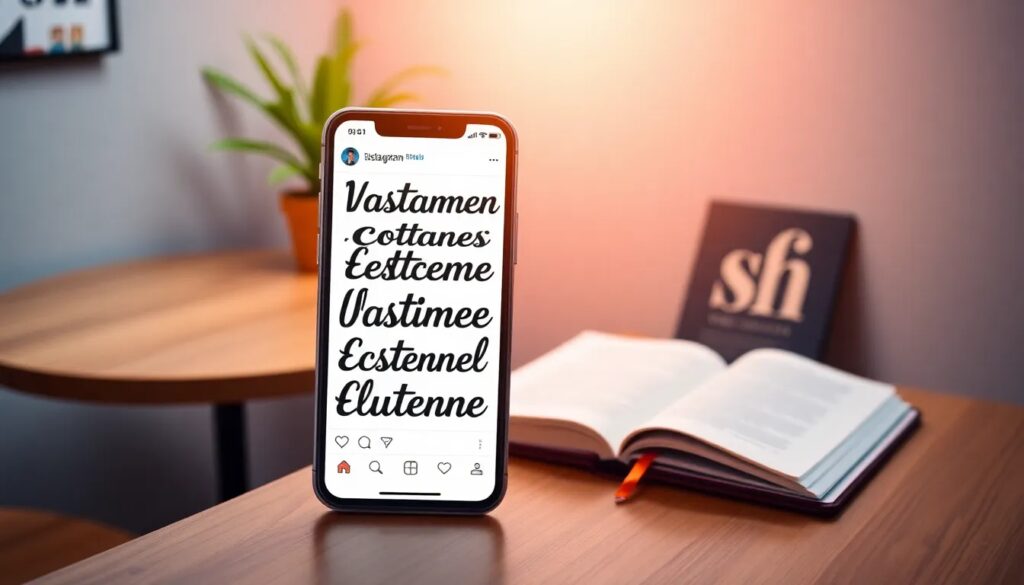
Tipografía en Instagram: cómo usarla y personalizarla
La tipografía en Instagram es un elemento esencial para destacar en esta plataforma visual. Usar diferentes estilos de texto puede ayudar a que tus publicaciones sean más atractivas y memorables. A través de diversas herramientas y aplicaciones, es posible personalizar la tipografía para que se ajuste a tu estilo personal o de marca.
En este artículo, exploraremos cómo funciona el conversor de letras para Instagram, los tipos de letras más populares, y las mejores aplicaciones para cambiar fuentes. También te daremos ideas creativas para usar tipografías que capturen la atención de tus seguidores.
¿Cómo funciona el conversor de letras para Instagram?
El conversor de letras para Instagram es una herramienta en línea que permite transformar tu texto en diferentes estilos tipográficos. Este tipo de herramientas utiliza el sistema Unicode para generar variaciones que son compatibles con Instagram y otras redes sociales.
Al utilizar un conversor, simplemente escribes el texto que deseas transformar y, en cuestión de segundos, obtendrás varias opciones de estilos para elegir. Estas transformaciones pueden incluir cursivas, negritas, y símbolos especiales. Una vez que decides el estilo que más te gusta, solo tienes que copiarlo y pegarlo en tu publicación de Instagram.
Además, muchos de estos conversores son gratuitos y no requieren registro, lo que los hace accesibles para cualquier usuario. Su uso se ha popularizado especialmente entre quienes buscan añadir un toque de creatividad a sus publicaciones.
¿Qué tipos de letras son las más usadas en Instagram?
En Instagram, algunas de las tipografías más usadas incluyen estilos cursivos, negritas y letras decorativas. Estas tipografías no solo aportan un estilo único, sino que también son fáciles de leer en dispositivos móviles. A continuación, te presentamos una lista con los tipos más populares:
- Cursivas: ideales para dar un toque elegante.
- Negritas: perfectas para enfatizar un mensaje.
- Decorativas: aportan un estilo único y divertido.
- Minimalistas: limpias y fáciles de leer.
- Vintage: evocan nostalgia y son muy llamativas.
La elección del tipo de letra también puede depender del mensaje que deseas transmitir. Por ejemplo, si estás promocionando un producto, una tipografía clara y moderna puede ser la más efectiva. En cambio, si deseas compartir una cita inspiradora, una letra cursiva puede añadir un toque especial.
¿Cómo personalizar fuentes de Instagram?
Personalizar la tipografía en Instagram es una forma efectiva de destacar tu contenido. Existen varias maneras de hacerlo, y aquí te mostramos algunas de las más populares:
- Utilizar generadores de fuentes en línea: como los conversores, te permiten crear texto único rápidamente.
- Apps de edición: aplicaciones como Canva o Over ofrecen herramientas de diseño que incluyen diversas tipografías.
- Combinaciones de emojis y fuentes: mezclar emojis con diferentes estilos de texto puede hacer que tu publicación destaque aún más.
- Uso de hashtags creativos: incluir hashtags relacionados con tu estilo puede atraer más atención.
Recuerda que la clave es encontrar un equilibrio entre creatividad y legibilidad. No todas las tipografías son adecuadas para todas las publicaciones, así que experimenta con diferentes estilos hasta encontrar el que mejor se adapte a tu contenido.
¿Qué son las letras para Instagram y para qué sirven?
Las letras para Instagram son estilos de texto que puedes utilizar en tus publicaciones y biografías para hacerlas más atractivas. Sirven para expresar tu personalidad, destacar información, o simplemente hacer que tu contenido sea más visualmente interesante.
Estas letras son especialmente útiles para empresas y marcas que buscan crear una identidad visual. Al utilizar tipografías únicas, puedes comunicar tus valores y estilo de una manera que resuene con tu audiencia. Además, las letras creativas pueden ayudar a aumentar el engagement al captar la atención de los usuarios al instante.
Por otro lado, las letras personalizadas pueden ser utilizadas en anuncios y promociones para destacar ofertas especiales y atraer a más clientes. Por lo tanto, son una herramienta clave dentro de tu estrategia de contenido en redes sociales.
Apps para cambiar de letra en Instagram: las mejores opciones
¿Cuál es la nueva tipografía de Instagram?
Recientemente, Instagram ha actualizado su tipografía a Instagram Sans, que se utiliza principalmente en su branding. Sin embargo, esto no limita a los usuarios, quienes pueden seguir utilizando diferentes estilos de fuentes a través de generadores y aplicaciones, brindando una gran flexibilidad en la personalización de su contenido.